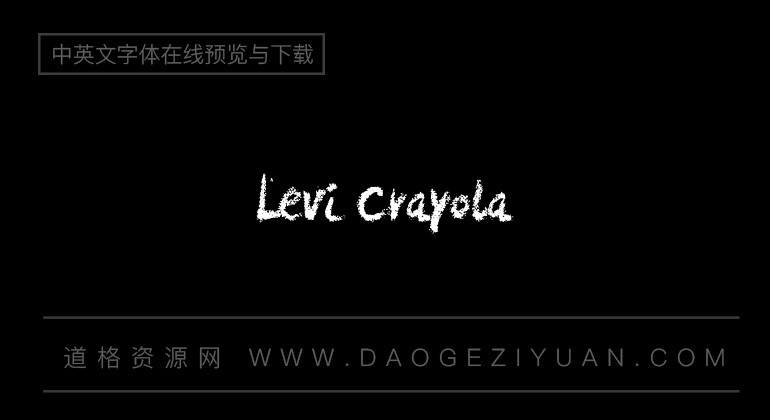
Levi Crayola
Levi Crayola 字体是一种手写风格的字体,其设计灵感来自于彩色蜡笔。这种字体的特点是字母的笔画有一定的粗细变化和倾斜,同时强调了手写的自然感觉和流畅性。Levi Crayola 字体适用于海报、卡片、标志、广告等多种应用场合,能够营造出轻松、有趣、活泼的视觉效果。 Levi Crayola 字体由设计师Levi Szekeres于2017年创建,目前已经广泛应用于许多设计项目中。该字体有多种格式可供选择,包括TrueType、OpenType和Web字体等,方便不同平台和应用程序使用。
Levi Crayola是一款非常不错的手写艺术字体,具有很好的视觉感,适合于文化类的宣传设计、商业类品牌的广告和产品包装设计以及个性化文字排版等较多场景。